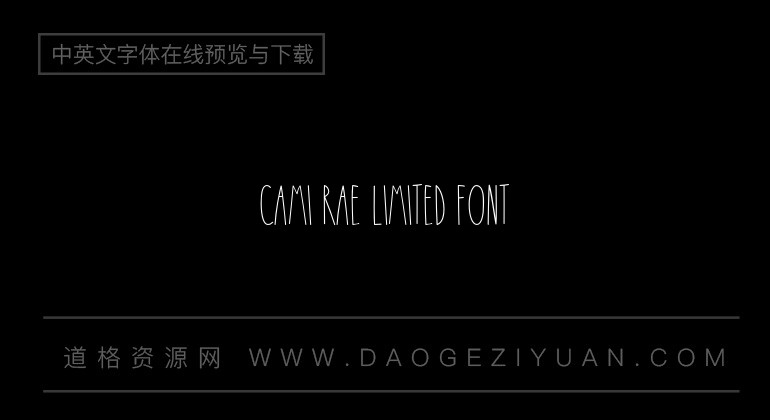
Cami Rae Limited Font 是一种手写体字体,其字形充满了自然、流畅和优美的特点。这种字体的设计灵感来自于手写字母的魅力,可以让你的设计感觉更加个性化和独特。 Cami Rae Limited Font 包含了大写字母、小写字母、数字和一些标点符号,它们都具有细腻的线条和独特的字形。这种字体非常适合用于个人博客、手写风格的海报、明信片、包装设计等场合,能够为你的设计添加一份温暖和亲切的气息。 Cami Rae Limited Font 可以在许多设计软件中使用,例如 Adobe Photoshop、Illustrator、InDesign 等等。这种字体的使用非常灵活,可以根据你的需要进行组合和排版,使得你的设计更加美观和有吸引力。内容介绍
Cami Rae limited Font是一款非常不错的手写艺术字体,具有很好的视觉感,适合于文化类的宣传设计、商业类品牌的广告和产品包装设计以及个性化文字排版等较多场景。